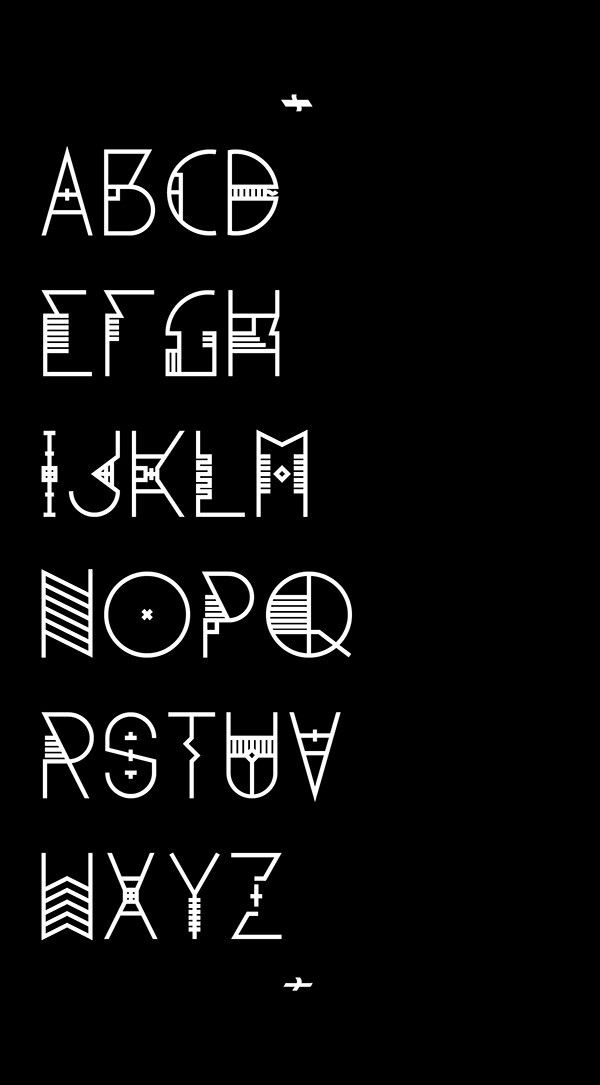
Трендовые шрифты 2020: где найти типографику?
Новое десятилетие раздвигает границы и рушит стереотипы в графическом дизайне. От простоты до ретро, от исчезающих символов до классической геометрии — в 2020 году можно все. В статье расскажем, как подобрать «почерк» для вашего бизнеса.
Как всегда оставаться в тренде
Особенность современных тенденций — в их широте, гибкости и отсутствии четких рамок. В типографике мирно уживаются противоречивые стили.
Поэтому, применив любой прием в логотипе, рекламной продукции или оформлении упаковки, вы можете не переживать, что через год перестанете быть актуальным.
Вот три лайфхака, как всегда оставаться в тренде:
- Создайте качественную базу. Делайте выбор в пользу простоты и лаконичности, которые не выходят из моды. Подберите многофункциональную графику, которая будет одинаково хорошо смотреться на эмблеме и билборде, на бланке и экране телефона.
- Позаботьтесь о смысле. Выбирайте начертания, которые соответствуют характеру бренда, и отличаются не только оригинальностью, но и смысловой нагрузкой.
Восемь главных трендов
1. Стиль семидесятых и восьмидесятых годов
Китч и неоновые цвета возвращаются в новом исполнении.
Задайте настроение при помощи яркой типографики.
Miami Vice
Широкие неоновые буквы из титров сериала 80-х «Miami Vice» похожи на шрифт Broadway D, который Моррис Фуллер Бентон разработал еще в 1927 году. Загрузите его за $19,95 и украшайте фильмы или постеры.
Alba
Стиль с оригинальным обтекаемым начертанием посвящен голливудской звезде Джессике Альбе. В личных целях Alba можно пользоваться свободно, а в коммерческих — заплатив $19,95.
Nasalization
Студию Typodermic Fonts вдохновила эмблема NASA 1975 года, которая и сейчас выглядит свежо благодаря лаконичности. Лицензия позволяет бесплатно использовать продукт для некоторых коммерческих целей, в частности, создания лого, плакатов или видеороликов.
Rotola TH Pro
Плотные жирные символы, разработанные Карлом-Хайнцем Ланге, можно приобрести за $40. Такая графика будет эффектно смотреться, к примеру, в заголовках на экране.
Liberta TA
Герберт Таннхаузер придумал Liberta для шрифтолитейного завода Typoart в ГДР на рубеже 60-х годов. Мягкий, но уверенный и элегантный «почерк» украсит рекламу или лого. Приобрести его можно за $40.
8th Avenue
На разработку трафаретного шрифта дизайнеров Our House Graphics вдохновили надписи на контейнерах для продуктов начала 50-х. Создатели советуют применять 8th Avenue для упаковки товаров и логотипов. Стоимость — $30.
6th Aniversario
Сжатые, вытянутые вверх буквы словно написаны от руки, но при этом легко читаются. Скачать работу Фернандо Аро можно за $21.
2. Ретро
Печатная и рукописная, с засечками и без — типографика в ретро-стиле обрела новое звучание. Она особенно актуальна для творческого бизнеса.
Aesthetic
Готика от Figuree Studio похожа на надпись на старой вывеске с причудливыми изгибами и завитками.
Aesthetic подойдет для фильма, плаката или стилизованного лого. Его стоимость — $12.
Curious Type
Бесплатный набор, созданный Джейсоном Форрестом, включает разные стили: психоделический с плывущими символами, геометричный с угловатыми, графику из пикселей и вариации на тему традиционной Helvetica.
Big Bro
Себастьян Тапиванаше предлагает бесплатный шрифт, который гармонично сочетает элементы ретро и современности. Big Bro подойдет экрана или постеров.
Groovy
HP Typework вдохновлялись типографикой 60-70-х годов: жирные рукописные буквы с завитками напоминают о винтажных афишах. Приобрести Groovy можно за $19.
The Banthink
Игривая неровная графика от Lettersiro Co создает неформальный стиль, который будет уместен как на лого, так и на одежде или вывеске. Стоимость — $15.
The Glarious
Разработанный Motokiwo рукописный шрифт с широкими штрихами формирует динамичный образ.
Купить The Glarious можно за $16.
Forbes
За $15 вы получите по-настоящему винтажную типографику, которая ассоциируется со старинными рукописями. Образ дополняют тщательно проработанные засечки.
Goosebumps
Разработка авторства Comicraft заставит дрожать любую надпись: все элементы словно покрыты пупырышками и слегка вытянуты. Скачайте Goosebumps за $19, чтобы украсить забавный плакат или сайт.
3. Минимализм
Этот мощный тренд не собирается сдавать позиции. Исчезающие символы и эксперименты с негативным пространством делают надписи легкими и эффектными.
Black rovers Font
Пандан Ванги придумал графику-загадку с исчезающими элементами и геометричным начертанием. В личных целях (например, для собственного сайта) вы можете пользоваться продуктом без ограничений. Для коммерческого применения необходимо приобрести лицензию.
Agnostic Font
Декоративную графику, разработанную Викторией и Виктором Струковским, украшают геометрические элементы.
Тонкие линии подойдут для разработки монограммы или надписи на упаковке. Стоимость — от $10.
QSansPro
Универсальные классические шрифты авторства Fontop позволят создавать стильные заголовки, рекламу и эмблемы. Тем более, что дизайнеры предусмотрели много вариантов — от сверхсветлого до сверхжирного. Скачивайте любой из них за $11.
Mofita
В Alit Design придумали элегантную округлую типографику. Купив Mofita за $15, вы сможете украсить лого, оформить цитаты или меню.
Munich Sans
В Eldertype Studio вдохновлялись минималистичными геометрическими формами. Получилось стильно и современно: тонкие вытянутые буквы одинаково хорошо подойдут для брендинга как кондитерам, так и юристам. Цена — $13.
4. Классика
Встречайте классику в новом исполнении: утонченное написание теперь выглядят не напыщенно, а легко и стильно. Универсальная типографика применима для максимального круга задач.
Classic Roman ™
Графика от Monotype Design Studio основана на базовых геометрических фигурах и удобочитаема. Скачать ее можно за $35.
Galano Classic
Разработка Рене Бидера тоже отдает дань геометрии и считается универсальной. Еще одно преимущество Galano Classic — десятки вариантов разного наклона и степени насыщенности. Каждый из них продается за $30.
George
Жирные округлые буквы с мягкими засечками создают легкий винтажный эффект. Эти изогнутые линии придадут элегантный вид логотипам, праздничным открыткам, рекламным объявлениям и многому другому. Авторство принадлежит Dharmas, цена — $13.
Chloe
Джош Оунби предлагает типографику с сильным характером. Контрасты насыщенности создают впечатление элегантности и уверенности. Скачать Chloe можно за $15.
5. Современность
Такие надписи узнаваемы по легкости, динамике, нарочитой небрежности и неожиданному использованию привычных элементов.
Codec Pro
Вдохновленные геометрией, Франческо Кановаро, Козимо Лоренцо Панчини и Андреа Тартарелли придумали оригинальное начертание с 11 вариантами — от тонкого до жирного. Codec Pro оживляют декоративные элементы: лигатуры и искусственное растягивание символов по горизонтали. Два шрифта можно загрузить бесплатно, остальные — за $30 каждый.
Impossible
Воплощение простоты от Ghuroba Studio: элегантный рукописный стиль со слегка «неидеальными» буквами. Загрузите его стандартную версию или курсив за $15 и применяйте для эмблемы, подписи к email, рекламы или дизайна продукции.
Nevrada
Острые засечки, плавные формы и изящные завитки от Aluyeah Studio придадут изюминку любому продукту — от сайта до постера. Стоимость использования в коммерческих целях — $20.
Cremona
Классика без засечек в исполнении Vultype Co подойдет для презентаций, визиток, брендинга.
Обычной версией Cremona можно пользоваться бесплатно, нестандартная стоит $20.
MODEKA
Рубленая минималистичная графика от Гатиса Вилакса выглядит легко и утонченно. Оригинальность ей придают сглаженные углы. Пользоваться MODEKA можно бесплатно.
MODERNIA
Далер Мухиддинов представил современную интерпретацию трафарета. Толстые прописные буквы смотрятся эффектно и самодостаточно. MODERNIA находится в свободном пользовании.
Sofia Font
Headstudio предлагают простые формы в сочетании с ультражирным написанием, которое придаст оригинальности брендингу. Загрузить Sofia Font можно бесплатно.
6. Засечки
Этот прием возвращается как символ доцифровой эпохи. Создайте эффект ностальгии и добавьте нотку теплоты в отношения с клиентами.
Recoleta
Мягкие формы от Latinotype словно отсылают к 70-м и передают дружелюбный характер текста.
Выбирайте из 14 вариантов Recoleta и воспользуйтесь бесплатной демо-версией для одного из них (остальные стоят $29).
Voga
Декоративный слегка сжатый «почерк» выглядит сдержанно и элегантно. Буквы прорисованы по принципу контраста — от тонкого к толстому, от плавного к острому. Разработчик (North Type) советует применять Voga для заголовков и других крупных форматов. Стандартная версия находится в свободном пользовании, две другие продаются за $35.
Magfirah
Сочетание классики, модерна и минимализма, а также необычные лигатуры придадут оригинальности и вдохновения любому продукту — от открыток до принта на футболках. Скачать Magfirah можно за $20.
Selvina
Классика с толстыми изгибами от Hanzel Studio Selvina напоминает заголовки в старых глянцевых журналах. Скачивайте Selvina за $18 и создавайте монограммы или презентации.
7. Чистая графика
Не хотите зависеть от трендов? Выбирайте минималистичную чистую типографику — это неизменно актуально.
Veneer Clean ™
Yellow Design Studio разработала легко читаемую графику с ноткой официальности. Разбавить это впечатление помогут иконки в стиле фанк, которые доступны бесплатно. Стоимость каждой версии Veneer Clean — $15.
Palomino Clean
Рукописный или машинописный, тонкий или акцентный — Елена Генова представила шрифты, которые украсят как официальный брендинг, так и креативные флаеры или открытки. Цена каждого из них — от $15.
Papua Font
Tosca Digital предлагает плавные формы, основанные на классической геометрии. Загрузите Papua Font за $10 — и убедитесь в его универсальности.
Mimi Typeface
Еще один продукт от Tosca Digital сочетает мягкие линии с острыми углами. Стоимость Mimi Typeface — $12.
Faldano Font
Если каждый символ вписать в квадрат, растянуть по горизонтали и сплющить по вертикали, получится оригинальный стиль, который создаст акцент в любом заголовке, на упаковке продукции или визитке.
Купите Faldano Font за $10, чтобы придать брендингу силу и уверенность.
Fox & Cat
Джо Агилар разработала бесплатную типографику с утонченной геометрией и эффектом воздуха. Изящное сочетание округлых и угловатых тонких линий украсит любой брендовый продукт — как с серьезным, так и с творческим характером.
8. Элегантность
Забудьте о вычурном дизайне: тонкие линии, простота и мягкие акценты всегда смотрятся современно.
Vaguely Fatal Font
Изюминка — в нарочитой тесноте между буквами, которые, кажется, вот-вот перекроют друг друга. Работу Unhinderedreams/Mind Confetti можно использовать свободно.
Oleo Font
Плавный «почерк» с акцентными засечками смотрится мягко, дружелюбно и создает легкий винтажный эффект. Чтобы применять Oleo в коммерческих целях, нужно приобрести лицензию или обратиться к дизайнеру Матиасу Ромеро.
Le Royale
Элегантная разработка от Salt&Pepper Designs — дань уважения классике с вкраплением модных тенденций.
Волнистые линии и оригинальная геометрия ассоциируются с непринужденной и теплой атмосферой. Цена Le Royale — $16.
Roihu
Семейство из 16 шрифтов (восемь вертикальных и восемь курсивных), созданное Микой Мелвас, выглядит современно и лаконично. Такое написание будет одинаково уместно как для плаката, так и для монограммы. Купить Roihu предлагают за $39.
Как узнать название шрифта
Заметили необычную графику, которая подойдет для вашего брендинга? Чтобы узнать, как она называется, сфотографируйте надпись (например, афишу или вывеску кафе) или сделайте скриншот экрана (если речь идет о сайте), а затем воспользуйтесь специальными онлайн-сервисами.
WhatTheFont
Ресурс, работающий на платформе My Fonts, сопоставит ваше изображение с более чем 133 тысячами начертаний. А приложение WhatTheFont для Apple или Android позволяет проводить поиск онлайн прямо с камеры телефона.
Font Identifier
Платформа Font Squirrel предлагает воспользоваться опцией распознавания: загрузите изображение или укажите его URL — и искусственный интеллект выдаст результаты.
WhatFontIs
Поиск по каталогу из более чем 600 тысяч работ. Сервис предложит вам около 60 вариантов, похожих на те, что вы ищете, а также ссылки на сайты, где их можно приобрести.
Font Matcherator
Ресурс отличается мощным поиском, который тщательно детализирует загруженные изображения и выдает максимально точные результаты.
Как создать шрифт самостоятельно
При помощи генераторов шрифтов вы можете разработать собственную графику и придать ей оригинальности.
Igfonts
Хотите персонализировать био в Instagram? Получите уникальную графику, чтобы выделить свой профиль. Введите текст — и сервис будет генерировать бесконечное количество вариантов.
CoolTextFonts
Ресурс создаст надпись на основе более чем 100 тысяч символов по стандарту Unicode: букв из кириллицы, латиницы и других алфавитов, цифр, символов и графики.
CoolFonts
Введите текст, выберите из нескольких десятков готовых шрифтов, добавьте желаемый размер, цвет и эффекты (например, тени или градиент) — и получите уникальное изображение.
Где найти типографику для коммерческого использования
Предлагаем несколько популярных ресурсов, на которых можно найти платные, бесплатные продукты или просто вдохновиться.
MyFonts
Обширная коллекция (больше 130 тысяч наименований) и расширенный поиск делают этот сервис один из самых лучших для поиска графики.
Fonts Google
В подборке Google — 977 семейств популярных шрифтов и традиционно удобный поиск с фильтром по категориям, языкам, трендам и другим показателям.
Fontbundles
Тщательно отобранные коллекции от модных дизайнеров. Каждую неделю разработчики предлагают скачать бесплатный шрифт.
Creative Fabrica
Больше 23 тысяч шрифтов и сотни тысяч графических элементов.
Удобная система поиска по категории или названию позволяет быстро получить нужный результат.
Pixelsurplus
Коллекция бесплатной типографики. Из недостатков сервиса — отсутствие поиска по категориям.
Behance
Онлайн-сообщество, где дизайнеры выставляют свои работы. Советуем использовать этот ресурс для вдохновения — здесь много креативных и оригинальных продуктов.
8 известных шрифтов и дизайнеры, которые их создали
Самые известные шрифты в мире встречаются практически везде. Когда вы становитесь дизайнером, все эти засечки и толщина штрихов начинают буквально выскакивать на вас, и вы начинаете узнавать их в окружающей среде. У каждого штриха, который вы видите, есть свой создатель, история и свои фанаты.
Посмотрите, как создавались некоторые из известных шрифтов, и на дизайнеров, которые своими смелыми шагами изменили наш визуальный мир.
Разработан: Максом Мидингером и Эдуардом Хоффманом
Стиль шрифта: без засечек
История создания: Швейцария, 1957 год, шрифтолитейная Haas.
Мидингер хотел стать художником, но его отец убедил его, что стоит сфокусироваться на более прикладной профессии. Мидингер взялся за дизайн шрифтов и создал спустя 30 лет вместе с Хоффманом Гельветику. Он предназначался для того, чтобы заполнить отсутствие нейтрального шрифта, подходящего для вывесок.
Где вы могли его видеть: Считается самым распространенным шрифтом в мире. Фильм «Гельветика». Брендинг American Apparel. Логотип Crate & Barrel. Логотип Lufthansa. Логотип Jeep. Система вывесок Нью Йоркского метро. И многое другое.
Разработан: Джамбаттиста Бодони
Стиль шрифта: с засечками
История создания: Италия, 1798. Бодони был нанят в качестве официального наборщика текстов для ряда итальянских герцогов. Эти герцоги были влюблены в его работу и предложили ему работу за печатным станком во дворце в Парме. В свое время его называли «дизайнер королей и король дизайнеров». После его смерти, его работы объединили и создали шрифт, который мы сейчас знаем как «Бодони».
Где вы могли его видеть: Один из самых старых шрифтов, который используется по сей день. Журнал Vogue. Постеры к мюзиклу «Mamma Mia!». Логотип Nirvana. Товарный знак Columbia Records.
Разработан: Виктором Лардентом
Стиль шрифта: с засечками
История создания: Англия, 1931. Был разработан по заказу британской газеты The Times после того, как шрифт дизайнера Стэнли Морисона подвергся критике из-за плохой читаемости. Морисон помогал штатному дизайнеру создавать Times New Roman, который затем разошелся по всему миру.
Где вы могли его видеть: Ваш доклад из университета. Набранный с двойным пробелом. 12 шрифтом. О
10 дизайнерских шрифтов для русскоязычных проектов
Мы живем в эпоху изобретений и находимся на пике развития человечества. Люди уже летают в космос, путешествуют в ранее недоступные точки земли, а домашние хлопоты взяли на себя разнообразные гаджеты.
Самое сложное сейчас − представить себе что-то совершенно новое, потому что все о чем бы вы не подумали, оказывается, уже кто-то придумал и создал минуту назад.
В этих реалиях художники и дизайнеры постоянно экспериментируют с объектами и инструментами вокруг себя. Создавать невероятные вещи − это вам не игрушки. Ведь чтобы придумать выдающийся дизайн логотипа, постера, флаера, буклета или даже фирменного бланка, необходим шрифт, который бы идеально подошел для конкретного продукта. Шрифт может сказать о продукте то, о чём не говорит его название — например, о его эксклюзивности, качестве или свежем взгляде создателя. И сегодня, команда Шуба Lab, поделится с вами 10 невероятно полезными шрифтами, которые вы сможете использовать в своих проектах для превосходного результата в будущем!
Отличный шрифт, который включает в себя 12 начертаний, множество различных лигатур и специальных символов. Единственный его минус заключается в том, что он платный (цена за весь комплект составит $595).
Это бесплатный гротескный шрифт. Он включает в себя 4 начертания: Light, Thin, Book, Regular. Шрифт с каждым днём набирает всё большую популярность и сейчас его можно назвать гельветикой (Helvetica) среди бесплатных шрифтов.
Это шрифт с засечками основан на Adobe Utopia и распространяется по свободной лицензии. Включает в себя 4 начертания. Несомненно пригодится дизайнерам, которые работают с большими объемами печатного текста.
Кириллический акцидентный шрифт, который авторы решили распространять абсолютно бесплатно. Шрифт был создан в 2008 году и с тех пор находится в свободном доступе. Шрифт включает в себя 1 начертание и особенно пригодится для дизайнеров печатной.
Бесплатный, гротеск. И он достаточно «молодой»: разработан был в 2012 году. В наборе всего 2 начертания, но в то же время шрифт бесплатный. Так что не смотрите дареному коню в зубы, а поскорее добавляйте в свою коллекцию.
Акцидентный шрифт с засечками. Лишь одно начертание — но его будет достаточно для заголовка вашего журнала или первого экрана продающей страницы.
Платный шрифт. Но два начертания вы можете скачать бесплатно и они отлично подойдут для оформления постеров, журналов и продающих страниц. Но за весь набор придется заплатить $279. Этот шрифт стоит своих денег, мы в этом убедились.
Акцидентный шрифт, который идеально подходит для дизайна логотипов, так или иначе связанных с кулинарией и гастрономией. Шрифт платный (49$) и в наборе всего одно начертание.
Огромное семейство шрифтов, включающее в себя 72 (!) начертания. В наборе можно найти шрифт для абсолютно любых целей. На данный момент шрифт продается со скидкой 90%! И сейчас все семейство Clio можно купить всего за $39.
Один из самых популярных платных гротесков в мире, а основан он был на известном шрифте Museo. Полный набор включает в себя 10 начертаний и приобрести себе его можно за 89$.
Шрифты, которые мы сегодня описали, станут хорошим подспорьем в создании дизайна ваших русскоязычных проектов.
Для того, чтобы первыми получать информацию о всех статьях и скидках от Шуба Lab − подписывайтесь на нашу рассылку http://eepurl.com/bmB4X1
Самые популярные шрифты / 7fonts.ru
Шрифты:
- A
- B
- C
- D
- E
- F
- G
- H
- I
- J
- K
- L
- M
- N
- O
- P
- Q
- R
- S
- T
- U
- V
- W
- X
- Y
- Z
- 0
- 1
- 2
- 3
- 4
- 5
- 6
- 7
- 8
- 9
- Необычные
- Мультфильмы
- Комиксы
- Округлые
- 70-80е
- Завивающиеся
- Вестерн
- Потертые
- Искаженные
- Гранж
- Огонь и лед
- Декоративные
- Печатающая машинка
- Армейские
- Рэтро
- Сетка
- Акцидентные
- Стильные
- Книжные
- Иностранные буквы
- Иероглифы
- Арабские
- Мексиканские
- Греческие
- Русские
- Техно
- Pop art
- LCD
- Фантастика
- Готические
- Инициалы
- Средневековые
- Современные
- Кельтские
- Обычные
- Sans serif
- Serif
- Моноширные
- Рукописные
- Каллиграфические
- Школа
- От руки
- Кисти
- Разные
- Граффити
- Картинки, иконки
- Ужасы
- Пришельцы
- Животные
- Азиатские
- Старинные
- Руны
- Эзотерические
- Фантастические
- Игры
- Фигуры
- Штрих-коды
- Природа
- Спорт
- Головы
- Дети
- ТВ, фильмы
- Логотипы
- Сексуальные
- Армия
- Музыка
- Праздники
- Валентинки
- Пасха
- Халлоуин
- Рождественские
- Другое
- Остальные
Популярные шрифты
- В начало
- 1
- 2
- 3
- 4
- 5
- 6
- 7
- В конец
- Bickham Script Two > Каллиграфические Количество просмотров: 305802
- Скачать шрифт
- One Fell Swoop > Каллиграфические Количество просмотров: 237075
- Скачать шрифт
- Corel > Остальные Количество просмотров: 232377
- Скачать шрифт
- Jellyka — Love and Passion > Валентинки Количество просмотров: 201149
- Скачать шрифт
- Most Wasted > Граффити Количество просмотров: 164258
- Скачать шрифт
- Painty Paint > Кисти Количество просмотров: 154638
- Скачать шрифт
- Days > Акцидентные Количество просмотров: 146468
- Скачать шрифт
- Android Nation > Фантастика Количество просмотров: 134576
- Скачать шрифт
- Smudgers > Гранж Количество просмотров: 108945
- Скачать шрифт
- Ariadna > От руки Количество просмотров: 106459
- Скачать шрифт
- Bebas > Sans serif Количество просмотров: 103271
- Скачать шрифт
- Phoenix > Огонь и лед Количество просмотров: 80682
- Скачать шрифт
- Argor Flahm Scaqh > Средневековые Количество просмотров: 94300
- Скачать шрифт
- Russian > Русские Количество просмотров: 89798
- Скачать шрифт
- Barcode Font > Штрих-коды Количество просмотров: 88133
- Скачать шрифт
- China cyrillic > Иероглифы Количество просмотров: 87889
- Скачать шрифт
- Code 128 > Штрих-коды Количество просмотров: 85852
- Скачать шрифт
- Comfortaa > Sans serif Количество просмотров: 81848
- Скачать шрифт
- English > Каллиграфические Количество просмотров: 79148
- Скачать шрифт
- Chopin Script > Каллиграфические Количество просмотров: 78194
- Скачать шрифт
- Satyr > Греческие Количество просмотров: 75741
- Скачать шрифт
- Propaganda > Русские Количество просмотров: 74618
- Скачать шрифт
- Pepsi > Остальные Количество просмотров: 74403
- Скачать шрифт
- Transformers > Фантастика Количество просмотров: 73328
- Скачать шрифт
- Argentine Bold > От руки Количество просмотров: 70930
- Скачать шрифт
- Mistral > Русские Количество просмотров: 70226
- Скачать шрифт
- WoW Plexus > Современные Количество просмотров: 70001
Рукописных шрифтов — Лучшие бесплатные шрифты для дизайнеров
Лучшие бесплатные шрифты: рукописные шрифты
41.
Cervanttis
Cervanttis — один из наших любимых бесплатных шрифтов, имитирующих фирменный стиль (Изображение предоставлено: Crella Marketplace / Creatype Studio / Mats-Peter Forss)С легким стилем и flow, Cervanttis Signature Script — один из наших любимых бесплатных рукописных шрифтов в этом списке и отличный выбор, если вы ищете сценарий рукописной подписи.Созданный Матсом-Питером Форссом, это один из лучших бесплатных шрифтов для передачи внешнего вида рукописного ввода, который хорошо подходит для логотипов, брендов, рекламы и сообщений в социальных сетях.
42. Timothy
Рукописные шрифты — это не только закрученные каракули (Изображение предоставлено Тимоти Гудманом) Рукописные шрифты не обязательно должны состоять из закрученных букв. В этом рисованном шрифте Timothy прописные буквы добавляют рукописный штрих. Тимоти был вдохновлен дизайнером Тимоти Гудманом, и мы думаем, что это будет хороший выбор при разработке приглашений.Обратите внимание, что для его загрузки вам необходимо указать адрес электронной почты.
43. Kavivanar
Этот наклонный рукописный шрифт основан на типичном тамальском почерке (Изображение предоставлено: Tharique Azeez / Font Squirrel)Разработанный Тарике Азизом, этот жирный рукописный шрифт был вдохновлен наклонными формами букв, характерными для типичного тамальского почерка. Помимо тамильского алфавита, он также включает латинские буквы.
44. Томатный суп
Томатный суп, сделанный вручную, идеально подходит для приглашений или воссоздания вида рукописной заметки (Изображение предоставлено: Pixel Surplus)Если вы когда-нибудь захотите воссоздать колючий почерк своего врача или, возможно, учитель, это шрифт для вас.Tomato Soup был создан Typed.one и лучше всего выглядит, когда текста меньше — мы бы не рекомендовали писать с его помощью отрывки.
45. Ambarella
Ambarella — красивый каллиграфический шрифт (Изображение предоставлено: Pixel Surplus) Ambarella — красивый бесплатный шрифт от Polem Studio.
Рукописный дизайн в стиле современной каллиграфии включает в себя различные росчерки, альтернативы и западноевропейские символы.
46. Nickainley
Nickainley — это бесплатный шрифт, основанный на винтажном почерке (Изображение предоставлено Seniors Studio)Nickainley — один из наших любимых бесплатных рукописных шрифтов.Этот шрифт Monoline выполнен в классическом винтажном стиле и включает символы верхнего и нижнего регистра, а также числа и знаки препинания. Созданный Seniors Studio, потенциальные варианты использования этого шрифта включают логотипы, футболки, фирменные бланки и вывески.
47. Shadows into Light
Этот бесплатный рукописный шрифт имеет закругленные края и приятный вид (Изображение предоставлено Google Fonts). Shadows Into Light — это работа шрифтового дизайнера Кимберли Гесвайн из компании Principal Design. Этот прекрасный рукописный шрифт с закругленными краями и аккуратными чистыми символами идеально подойдет для придания индивидуальности вашим проектам.
48. Pacifico
Pacifico — один из самых непринужденных бесплатных шрифтов в мире (Изображение предоставлено Google Fonts)Pacifico — забавный рукописный шрифт с кистями, вдохновленный американской культурой серфинга 1950-х годов. Этот шрифт с открытым исходным кодом был одним из величайших вкладов в сообщество свободного программного обеспечения покойного дизайнера Вернона Адамса.
49. Cute Punk
Cute Punk — это бесплатный шрифт, основанный на почерке, но с изюминкой ((Изображение предоставлено: Flue)Cute Punk предлагает яркий, молодой и полностью современный взгляд на рукописный шрифт.Этот бесплатный шрифт, наполненный поразительным, почти геометрическим ощущением, создан Флоу, дизайнером и иллюстратором из Братиславы, Словакия.
50. Yellowtail
Бесплатный шрифт Yellowtail отличается классическим подходом к рукописным шрифтам кистью (Изображение предоставлено Google Fonts) Yellowtail — это плоский шрифт старой школы, напоминающий классические шрифты 1930-х годов, такие как Gillies Gothic и Kaufmann.
Разработанный институтом типографики Astigmatic, сочетание соединительных и несвязных букв придает ему уникальный вид и обеспечивает хорошую читаемость.
Следующая страница: Бесплатные винтажные и ретро шрифты
5 обязательных инструментов для креативщиков
Ролик Moleskine Classic Plus …
ЯБЛОЧНЫЙ КАРАНДАШ ДЛЯ IPAD PRO …
12,9-дюймовый iPad Pro Wi -Fi …
Б / у Fujifilm X-Pro2 Body
шрифтов Sans-serif — Лучшие бесплатные шрифты для дизайнеров
Лучшие бесплатные шрифты: шрифты без засечек
21. Skye
Такой же универсальный, сколь и красивый Skye выбивает другие бесплатные шрифты на шесть (Изображение предоставлено Джонатаном Хиллом) Сочетая в себе гуманистические и геометрические элементы, Скай — это универсальный шрифт без засечек, который прекрасно сочетает узкие закругленные буквы с тонкими квадратными деталями.Разработанный Джонатаном Хиллом, он идеально подходит для использования в проектах цифрового дизайна, включая названия фильмов, пользовательские интерфейсы и Интернет.
Также читайте: Лучшие курсивные шрифты прямо сейчас
22. Obrazec
Obrazec — один из самых смелых и надежных бесплатных шрифтов в мире (Изображение предоставлено Илья Захаров)Obrazec — бескомпромиссный шрифт в индустриальном стиле. serif создал Илья Захаров. Этот прочный и уверенный шрифт — один из лучших бесплатных шрифтов для придания силы и индивидуальности вашим проектам по брендингу, независимо от того, работаете ли вы над дизайном логотипа, рекламными материалами или рекламой.
23. Archive Grotesk
Free Archive Grotesk — один из лучших бесплатных шрифтов для приглашений, календарей и других канцелярских принадлежностей (Изображение предоставлено Томасом Кларксоном) Созданный Томасом Кларксоном, Free Archive Grotesk — это чистый и минималистичный шрифт без текста, который включает прописные, строчные и цифры. Это один из тех бесплатных шрифтов, который подойдет для всего: от заголовков и оформления страниц журнала до приглашений, календарей, открыток и модных дизайнов.
24.Animosa
Animosa чистая, современная и привлекающая внимание (Изображение предоставлено Стефано Джилиберти)Animosa — это чистый современный шрифт без засечек с широким спектром уникальных символов. от Созданный Стефано Джилиберти, этот шрифт доступен в пяти весах и включает 93 языка и 508 глифов. Это один из лучших шрифтов, которые мы видели, чтобы привлечь внимание читателя к странице и удерживать его там.
25. Red Hat
Fedora не требуется (Изображение предоставлено Red Hat)Если вы не пользуетесь Linux и открытым исходным кодом, то это имя не будет иметь большого значения для вас; не беспокойтесь об этом слишком сильно, потому что все, что нас интересует здесь, это шрифт, разработанный Джереми Микелем.Он вдохновлен американскими шрифтами без засечек, доступен в двух оптических размерах и разной плотности.
26. Public Sans
Разумный шрифт sans для серьезных проектов (Изображение предоставлено: Public Sans) Основанный на Libre Franklin и созданный как часть системы веб-дизайна США, Public Sans — это бесплатный веб-шрифт с открытым исходным кодом, разработанный для использования в интерфейсах, тексте и заголовках.
Это сильный, строгий шрифт с нейтральным внешним видом, большим количеством начертаний и минимальным количеством причуд; идеально подходит для серьезных проектов, когда вы пытаетесь избежать ненужного отвлечения внимания.
27. Loki
Loki отлично подходит для заголовков (Изображение предоставлено Wild Picks)Loki — это своего рода гибридный шрифт, это рукописный скрипт кисти с базой без засечек и довольно приятными изгибами. Созданный Кришьянисом Мезулисом и Иевой Мезуле, он предназначен для заявлений и особенно хорошо работает с большими заголовками.
28. Salt
Salt удивительно атмосферный (Изображение предоставлено Машей Чупровой)Атмосферный шрифт Salt имеет два веса: обычный и жирный.Он создан Машей Чупровой и имеет «низкий центр тяжести». Обратите внимание, что вам нужно будет указать свое имя и адрес электронной почты в Pixel Surplus, чтобы загрузить его бесплатно.
29. Alcubierre
Этот чистый, минималистичный шрифт подходит для различных целей (Изображение предоставлено Web Designer Depot) Геометрический шрифт без засечек Alcubierre — это работа дизайнера Мэтта Эллиса.
Следуя по стопам его оригинального бесплатного шрифта Ikaros, этот чистый минималистичный шрифт подходит для самых разных целей.
30. Большой Джон / Тонкий Джо
Эти два шрифта без засечек отлично работают вместе (Изображение предоставлено Ионом Люсином)Большой Джон был создан дизайнером Ионом Лучином для личного использования. В конце концов, он решил поделиться им на Behance, а затем добавил сверхлегкий родственный шрифт: Slim Joe. Оба шрифта заглавные, и в сочетании друг с другом они отлично контрастируют. Эти бесплатные шрифты идеально подходят для заголовков и заголовков.
31. Titillium Web
Titillium — это бесплатный шрифт, который лучше всего работает с большими размерами (Изображение предоставлено: Accademia di Belle Arti di Urbino / Cufon Fonts) Что касается бесплатных шрифтов, Titillium имеет очень респектабельную родословную, рожденную от Проект шрифтового дизайна в Академии прекрасных искусств Италии в Урбино.Каждый учебный год над проектом работают около десятка студентов, развивая его и решая задачи.
«Titillium был моим любимым шрифтом в течение нескольких лет, — говорит Роб Хэмпсон, руководитель отдела дизайна The Bot Platform, платформы для создания ботов в Messenger. «Он четкий, современный и доступен в широком диапазоне толщины. На мой взгляд, он лучше всего подходит для больших размеров; например, для заголовков. Тем не менее, при тщательном рассмотрении его можно использовать в качестве основного шрифта».
32.Atami
Atami — жирный шрифт с современным дизайном (Изображение предоставлено Эндрю Херндон).Atami — довольно экспериментальный шрифт, который бывает двух разной толщины и трех стилей. Созданный Эндрю Херндоном, мы думаем, что это будет особенно хороший выбор для создания плакатов и логотипов.
33. Chivo
Chivo — один из самых привлекательных бесплатных шрифтов (Изображение предоставлено: Omnibus Type) Chivo — гротескный шрифт, который идеально подходит для заголовков и других страниц, на которых вы хотите привлечь внимание.
Уверенный и элегантный, он был выпущен в четырех вариантах веса с соответствующим курсивом. Этот бесплатный шрифт — работа Эктора Гатти и команды Omnibus-Type.
34. Comfortaa
Бесплатный шрифт Comfortaa может хорошо работать в дизайне логотипа (Изображение предоставлено Google Fonts)Comfortaa — это округлый геометрический шрифт без засечек, предназначенный для больших размеров. Созданный Йоханом Аакерлундом, инженером-проектировщиком Датского технического университета, это простой, красивый шрифт, который включает в себя большое количество различных символов и символов.В рамках проекта улучшения шрифтов Google, последние обновления семейства включают добавление кириллицы и поддержку вьетнамского языка.
Дэвид Эйри, графический дизайнер и писатель из Северной Ирландии, входит в число его поклонников. «Многие бесплатные шрифты требуют слишком много работы, чтобы убрать все точки, но это не значит, что вы не можете найти хорошие варианты», — говорит он. «Для проекта айдентики я использовал Comfortaa в качестве основы для индивидуального словесного знака.
До и после действительно сильно отличаются, но работа Йохана дала мне отличную основу, и клиент любит результат.»
35. Noto Sans
Один из самых гибких бесплатных шрифтов, Noto Sans поддерживает более 800 языков (Изображение предоставлено Google Fonts)Noto Sans — это бесплатное семейство шрифтов, разработанное Google, поддерживающее более 100 систем письма , 800 языков и сотни тысяч символов. Шрифты Noto призваны быть визуально гармоничными для разных языков, с совместимой высотой и толщиной штриха. Это семейство включает обычные, полужирные, курсивные и полужирные курсивные стили, а также родственное семейство шрифтов с засечками , Noto Serif.
36. HK Grotesk
HK Grotesk — один из наших любимых бесплатных шрифтов для создания мелкого текста (Изображение предоставлено Hanken Design Co) HK Grotesk — это шрифт без засечек, вдохновленный классическими гротесками, такими как Akzidenz Grotesk, Univers, Trade Gothic и Gill Sans. Он был разработан Hanken Design Co с целью создания удобного и различимого шрифта, подходящего для небольшого текста.
Недавно он расширил свою языковую поддержку, добавив кириллические символы (болгарский, русский и сербский).
37. Aileron
Один из наших любимых гибридных бесплатных шрифтов, Aileron — удобный выбор для чтения на экране (Изображение предоставлено: Tipotype)Aileron — универсальный, неогротескный шрифт без засечек, который находится где-то между Helvetica и Univers . Созданный Сорой Сагано, дизайнером Tipotype, он призван предоставить читателям высокий уровень визуального комфорта. Он доступен в 16 вариантах веса, от сверхлегкого до черного.
38. Ubuntu
Ubuntu — это специально разработанный бесплатный шрифт для использования на экране (Изображение предоставлено: Ubuntu / Dalton Maag) Этот бесплатный шрифт был специально создан, чтобы дополнить тон голоса Ubuntu, операционной системы Linux для персональные компьютеры, планшеты и смартфоны.Разработанный производителем шрифтов Далтоном Маагом, он использует функции OpenType и для наглядности на настольных и мобильных экранах намекается вручную.
39. Clear Sans
Кто знал, что Intel делает бесплатные шрифты? (Изображение предоставлено Intel)Clear Sans — это универсальный шрифт, разработанный корпорацией Intel с учетом удобства чтения на экране. Этот бесплатный шрифт, подходящий для экрана, печати и Интернета, отличается минимизированными символами и слегка узкими пропорциями, что делает его отличным выбором для дизайна пользовательского интерфейса, от коротких надписей до длинных отрывков.
40. Source Sans Pro
Первый набег Adobe на шрифт с открытым исходным кодом, Source Sans Pro — один из самых популярных бесплатных шрифтов дизайнерского сообщества (Изображение предоставлено Adobe) Выпущенный в 2012 году, Source Sans Pro был первым шрифтом с открытым исходным кодом. семейство шрифтов для Adobe, и оказалось очень популярным. Он задумывался как классический гротескный шрифт с простым, непритязательным дизайном, предназначенный для удобной работы в пользовательских интерфейсах.
Он был разработан Полом Д. Хантом, который продолжает работать шрифтовым дизайнером в Adobe.
Source Sans Pro — один из любимых бесплатных шрифтов Джеймса Холлингворта, цифрового дизайнера и иллюстратора высокого уровня из Бата, Великобритания. «Это такой солидный и надежный шрифт, который можно использовать в дизайнерской работе», — с энтузиазмом говорит он. «Я сам страдаю дислексией, поэтому считаю, что этот шрифт очень легко читать, и он отлично работает в пользовательских интерфейсах».
Также прочтите: Шрифты, которыми должен владеть каждый графический дизайнер
Следующая страница: Бесплатные шрифты для рукописного ввода
5 обязательных инструментов для творчества
Moleskine Classic Plus Roller…
APPLE PENCIL FOR IPAD PRO …
12,9-дюймовый iPad Pro Wi-Fi …
Б / у Fujifilm X-Pro2 Body
10 лучших бесплатных наборов шрифтов для графических дизайнеров
Если вы графический дизайнер, выбор шрифтов для использования может быть сложной задачей.
Однако мы здесь, чтобы помочь, и эти бесплатные комплекты шрифтов объединяют сотни фантастических шрифтов в одном месте. Это означает, что вы легко найдете то, что вам нужно.
Google Fonts — самый популярный каталог для встроенных веб-шрифтов.
Многие дизайнеры считают это бесценным ресурсом. Однако, имея в реестре около 900 шрифтов, бывает сложно выбрать, какие из них загружать.
Typewolf ежегодно собирает коллекцию из 40 лучших шрифтов Google.В этот пакет входят шрифты от известных дизайнеров шрифтов, которые имеют различную толщину и стили. На сайте также указано, какие шрифты лучше всего подходят для основного текста.
Все шрифты бесплатны как для коммерческого, так и для личного использования.Вы можете загрузить каждый шрифт по отдельности или перейти на его страницу Google Fonts. А если вы подпишетесь на информационный бюллетень Typewolf, вы сможете загрузить все 40 в одном zip-файле.
TheHungryJPEG — популярный веб-сайт с дизайнерскими ресурсами.
Он предлагает высококачественные шрифты, графику, стоковые фотографии, темы и шаблоны. Хотя большинство ресурсов не являются бесплатными, TheHungryJPEG предлагает набор из 26 шрифтов стоимостью 104 доллара, который стоит всего лишь пост в социальных сетях.
Большинство гарнитур в этом пакете — это экранные и скриптовые шрифты.Они хорошо подходят для крупномасштабной печатной графики, онлайн-сообщений и приглашений.
Например, Echizen — это нарисованный вручную шрифт, который отлично смотрится в макетах социальных сетей.
Если ваш следующий дизайн-проект выполнен в стиле ретро, вам понравится пакет Ultimate Old-School PC Fonts.
Эти шрифты — потрясающее воспроизведение шрифтов с первых дней развития компьютеров.Те, кто владел компьютерами в 1980-х, мгновенно узнают символы, созданные по образцу компьютеров IBM, устройств DOS и встроенного BIOS.
В этом пакете 81 набор символов.Некоторые из них имеют многоязычную поддержку через Unicode. Все эти файлы бесплатны для личного и коммерческого использования, если вы приписываете их дизайнеру.
Каждый из них можно загрузить отдельно или в виде небольшого zip-файла.На сайте также есть средство предварительного просмотра, которое позволяет вам тестировать шрифты.
Пакет Type Lovers Bundle — это бесплатная подборка из 20 стильных шрифтов от Dreambundles, сервиса, который предоставляет пакеты ресурсов для дизайна.Все эти шрифты различаются по стилю и бесплатны для коммерческого использования.
В этом паке есть шрифты, которые подходят для самых разных ситуаций.Mosk — это чистый шрифт без засечек с девятью плотностями, а Selima Script — это скрипт кисти, который хорошо работает поверх фотографий природы и пейзажей.
В этом паке участвовали разные художники и дизайнеры.Если вам нравится определенный шрифт в пакете, вы можете получить доступ к сайту дизайнера для других работ, которые они сделали.
Просматривая «Несокрушимый шрифт», вы быстро заметите, что у большинства шрифтов есть звездочка.Эти звездочки являются частью названия шрифта. Художник Оуэн Эрл, который разработал эту фабрику, использует их как способ выделиться.
В Indestructible Type есть множество уникальных архетипических шрифтов, которые невероятно универсальны.Gnomon * — жирный шрифт для крупномасштабного дизайна. Bodoni * — это шрифт с засечками, предназначенный для чтения любого размера. Хотя No Tears — это производная от Comic Sans, которая очищена.
Все шрифты на Indestructible Type используют модель «плати сколько хочешь» и по сути бесплатны.Если вы хотите сделать пожертвование проекту, вы можете оставить сумму при оформлении заказа.
В 1668 г.Джон Фелл, епископ из Оксфорда, разработал набор шрифтов, которые он хотел использовать в христианских публикациях и текстах. После его смерти в 1686 году Оксфордский университет сохранил его шрифты и в течение нескольких десятилетий начал издавать в его стиле.
В 2000-х итальянский инженер Игино Марини начал воссоздавать типы Fell в виде файлов современных шрифтов.Здесь представлены 13 ярких шрифтов с засечками, точно воспроизводящие его стили. Все они собраны в одном zip-архиве. Все они бесплатны, если вы приписываете их дизайнеру.
Не каждый дизайнер может сказать, что использует шрифт, разработанный в 1600-х годах, но теперь это возможно.
Ten By Twenty — это набор типографских проектов английского дизайнера Эда Мерритта.На его сайте вы найдете девять буквенно-цифровых шрифтов и один знаковый шрифт.
Его стили варьируются от готовых к публикации шрифтов с засечками, таких как Jura, до интересных блочных дисплеев, таких как Tödi.Его шрифты скачали более 1,5 миллиона раз. Все они лицензированы по лицензии открытого шрифта, поэтому бесплатны для всех типов использования.
Он продает их все по схеме «плати сколько хочешь».Если вы обнаружите, что вам действительно нравится использовать один из его шрифтов, вы можете вернуться позже и заплатить небольшую сумму.
8.Linux Libertine Fonts [битый URL-адрес удален]
Всего два шрифта, это самый маленький набор в этом списке.Тем не менее, оба они очень полезны.
Шрифты Linux Libertine предназначены для замены стандартных шрифтов Windows и Mac.Следовательно, они хорошо оптимизированы для дизайна UI / UX, обработки текста и публикации текста.
Libertine и Biolinum имеют чистые цифры, заглавные буквы и истинные дроби.Файлы доступны в tgz-архиве, и вот как извлечь файлы из обычных архивов, если вам нужно узнать больше.
Если вы творческий профессионал, есть несколько причин купить Adobe Creative Cloud.Наличие учетной записи CC дает вам неограниченный доступ к Adobe Fonts, библиотеке из более чем 14 000 шрифтов от Typekit.
Adobe Collections — это 30 бесплатных пакетов шрифтов, полученных из библиотеки шрифтов.Каждый пакет подбирается профессионалами-дизайнерами для конкретного использования. Есть коллекции для уличных планировок, для создания уличных указателей и материалов для активизма.
Если вы найдете пакет шрифтов, который вам нравится, все, что вам нужно сделать, это активировать его в своей учетной записи.Все включенные шрифты будут добавлены в вашу библиотеку CC.
Velvetyne Font Foundry или VTF — одна из самых ярких и необычных коллекций, которые вы увидите в Интернете.Вы найдете широкий спектр шрифтов, от готического шрифта, такого как Blocus, до пиксельного шрифта в стиле панк, такого как Terminal Grotesque.
Шрифты в этой коллекции созданы разными дизайнерами, но все они бесплатные.Это означает, что они имеют открытый исходный код, поэтому вы можете их модифицировать, изменять и использовать по своему усмотрению. Вы также можете свободно распространять отредактированные версии шрифтов.
Вы можете скачать любой из шрифтов в формате zip прямо с сайта.
Больше шрифтов и больше удовольствия
Вышеупомянутые бесплатные наборы шрифтов — отличные ресурсы для получения.Но если вы все еще не нашли свой идеальный шрифт, вот еще несколько веб-сайтов, где вы можете найти бесплатные шрифты. И если вы обнаружите, что описания этих шрифтов сбивают вас с толку, мы ранее объяснили наиболее важные термины типографики.
Начало работы с WPS Office: как перейти с MicrosoftWPS Office — популярная альтернатива Microsoft Office, отчасти благодаря тому, насколько легко переключиться.
Об авторе Ванн Висенте (Опубликовано 17 статей)Ванн — специалист по банковскому делу и финансам, увлеченный Интернетом. Когда он не занят подсчетом цифр, он, вероятно, ищет в Интернете еще один странный (или полезный!) Веб-сайт.
Больше От Ванн ВисентеПодпишитесь на нашу рассылку новостей
Подпишитесь на нашу рассылку, чтобы получать технические советы, обзоры, бесплатные электронные книги и эксклюзивные предложения!
Еще один шаг…!
Пожалуйста, подтвердите свой адрес электронной почты в письме, которое мы вам только что отправили.
Лучшие 87 шрифтов, которые должен скачать дизайнер
Шрифты для дизайнеров являются основным ресурсом. Только если вы примете во внимание манию типографики и у вас будет отличный аргумент в пользу разумного использования шрифтов.
Веб-шрифты в определенный момент кажутся скучными. С помощью @ font-face вы можете вставить любой шрифт на сайт и придать ему более интересный стиль.
Итак, допустим, вы не веб-дизайнер, вы скорее графический дизайнер, вы делаете качественные логотипы и другие интересные вещи. У вас должны быть лучшие шрифты для логотипов, если вы не являетесь довольно изысканным дизайнером и не создаете собственный шрифт для каждого проекта, над которым работаете.
При этом проверьте эти лучшие шрифты для дизайнеров, загрузите их, потому что большинство из них бесплатны, поищите файл readme от автора, чтобы узнать, где их можно использовать, и, возможно, купите некоторые из них в списке, которые являются шрифтами премиум-класса.
Лучшие шрифты для дизайнеров
Пришествие
Аниверс
Это семейство шрифтов OpenType состоит из обычных, курсивных, полужирных и маленьких заглавных букв и имеет несколько хороших функций OpenType. Помимо лигатур, контекстных альтернатив, дробей, устаревших / табличных числительных, Anivers также имеет функцию «case» для чувствительных к регистру форм и табличных чисел… так что Anivers может легко вычислять числа.
Получите 300+ бесплатных подарков на ваш почтовый ящик!
Подпишитесь на нашу рассылку и получите более 300 дизайнерских ресурсов за первые 5 минут в качестве подписчика.
Спасибо!
Требуется еще один шаг. Проверьте свой почтовый ящик на наличие электронного письма с подтверждением информационного бюллетеня.
Шрифт Densia Sans
Densia Sans — один из дизайнерских шрифтов в этой статье. Это экономичный шрифт без засечек, разработанный Harbor Type для использования в размерах от 6 до 14 пунктов. Его высокая высота по оси x и узкая ширина позволяют ему сиять в очень ограниченном пространстве.
Densia Sans не только экономит место, но и имеет полный набор из 820 символов, включая заглавные буквы, формы с учетом регистра, пропорциональные и табличные числа, старшие, подчиненные и дроби. Кроме того, его набор символов поддерживает более 30 языков.
Бебас
Bell Centennial
Разработанный Мэтью Картером из Mergenthaler специально для AT&T для замены Bell Gothic гарнитурой, в которой эффективно использовалась технология цифрового набора, Bell Centennial имеет дизайн шрифта, который имеет на несколько строк на страницу больше, чем Bell Gothic, сокращает количество обращений к информации из-за своего значительно более высокая читаемость в неблагоприятных условиях печати, что позволяет компании AT&T экономить многие миллионы долларов в год.
Graviola Regular
Graviola — это шрифт без засечек с полукруглыми концами, которые придают ему мягкий и дружелюбный вид. Семейство шрифтов имеет 8 отдельных толщин, от тонкого до черного, курсив планируется добавить в ближайшем будущем.
Наличные
Moderne Sans
Moderne Sans — это чистый шрифт без засечек, который можно бесплатно загрузить, разработанный Мариусом Кемпкеном.
Moderne Sans — бесплатный шрифт, вдохновленный типографикой 1920-х годов.Этот шрифт основан на прописных буквах, но я также создал строчные буквы, цифры и некоторые альтернативные буквы.
Coolvetica
Реклама
Coolvetica — это начертанный с нуля шрифт без засечек, вдохновленный дизайном американского логотипа 1970-х годов. Это была эпоха, когда все модифицировали Helvetica, добавляя причудливые локоны, смешанный регистр и эффекты.
Coolvetica воссоздает стиль надписей 1970-х годов с очень плотным кернингом и необычными завитками.Хвосты на R и a были опущены, чтобы обеспечить еще более тесный интервал. Он определенно не предназначен для установки абзацев в тексте книги — Coolvetica — это чистый дисплейный шрифт, предназначенный для больших, забавных заголовков и заголовков.
Фертиго
Fonesia Бесплатный шрифт
СемействоFonesia доступно в трех вариантах: Light, Regular и Bold. В этом первоначальном выпуске он по-прежнему содержит стандартный глиф: прописные и строчные буквы, числа, знаки препинания и некоторые символы.
Шрифт Shania Script
Shania Script Typeface — это современный каллиграфический шрифт со свободно плавной и подвижной базовой линией. Он имеет непринужденный, но элегантный вид, и его можно использовать для различных целей, таких как логотипы, приглашения на свадьбу, футболки, фирменные бланки, плакаты, значки и многое другое.
Shania Script Typeface включает 432+ глифов и 194 альтернативных символа, включая начальные и конечные буквы, альтернативные символы, лигатуры и поддержку нескольких языков.
Fontin Sans
Fontin Sans был разработан, чтобы быть подходящим без компаньона для Fontin.С красивым классическим внешним видом он идеально подойдет.
Бесплатная гарнитура Ikaros
Ikaros — это бесплатный современный минималистичный шрифт, созданный Мэттом Эллисом. Вы можете скачать его и использовать в своих проектах.
ITC Франклин Gothic Heavy
Фрутигер
В 1968 году Адриану Фрутиже было поручено разработать систему указателей и указателей для нового аэропорта Шарль де Голль в Париже. Он создал Frutiger, шрифт, характер которого вписался в современную архитектуру аэропорта.
Frutiger не является ни чисто построенным, ни декоративным, его формы разработаны таким образом, что каждый отдельный персонаж легко и быстро узнается даже на расстоянии. Такая четкость и разборчивость делает Frutiger идеальным шрифтом для вывесок и других приложений, где четкость символов имеет большое значение.
Шрифт Qontra Sans Serif
Футура
Futura — это полностью разработанный прототип геометрического сансерифа двадцатого века.
Форма древняя, греческие капители были начертаны критянами двадцать пять веков назад, во времена Пифагора, в Кодексе Гортина, имперскими римлянами, особенно в гробнице Сципиона, архитекторами классического возрождения в Лондоне восемнадцатого века. , которые легли в основу первого шрифта Sanserif Caslon в 1817 году.
Заголовок
BERNIER ™ Free Typefamily
Bernier — это небольшое семейство шрифтов, созданное Райаном Пиа.У Bernier есть три разных стиля, и это идеальный выбор для винтажного или олдскульного дизайна.
Семейство шрифтов Brayden
Brayden Family — это семейство скриптовых шрифтов, которые, вместе взятые, создают широкий выбор для художника или дизайнера. Это семейство шрифтов — одно из новейших предложений AF Studio. Возможности включают использование контекстных и стилистических альтернатив, контекстных штрихов и лигатур. Панель глифов обеспечивает доступ к еще большему количеству альтернатив.
В путь
Шрифт Break Free
Break — это современное семейство шрифтов, разработанное Раджешем Раджпутом и содержащее пять начертаний от полужирного до сверхлегкого, верхнего и нижнего регистра, цифр и символов.
Кенийский кофе
Kenyan Coffee — это шрифт с узким заголовком, созданный в 1999 году. В 2011 году Kenyan Coffee был перестроен и расширен до более крупного семейства шрифтов.
Музей
Это семейство шрифтов OpenType, которое является одним из лучших шрифтов нашего времени, имеет пять весов и поддерживает языки CE и даже эсперанто.Помимо лигатур, контекстных альтернатив, стилистических альтернатив, дробей и пропорциональных / табличных фигур MUSEO также имеет функцию «case» для чувствительных к регистру форм.
Neue Helvetica
Оптимус Принцепс
Проксима Нова
Proxima Nova устраняет разрыв между такими шрифтами, как Futura и Akzidenz Grotesk. В результате получился гибрид, сочетающий современные пропорции с геометрическим внешним видом.
Рислинг
Роквелл Экстра Полужирный
Стропа
Steelfish
Steelfish — это семейство сокращенных шрифтов для заголовков, созданное его автором в 2001 году.Оригинальный крой включал обычный, жирный и контурный стили. Steelfish был в порядке, но он нуждался в хорошей настройке, чтобы хорошо выступить в качестве веб-хедлайнера в 2010-х.
После перестройки автор расширил его до семи весов с курсивом. Вес оригинального Steelfish Bold больше похож на новый Steelfish Extra-Bold; имейте это в виду, если вы заменяете старую. Обычный, курсив, полужирный, полужирный курсив, экстра полужирный, экстра полужирный курсив и абрис — бесплатные.
С его помощью, как и с другими лучшими дизайнерскими шрифтами в этой статье, вы можете создавать дизайн шрифтов, который впечатлит ваших клиентов.